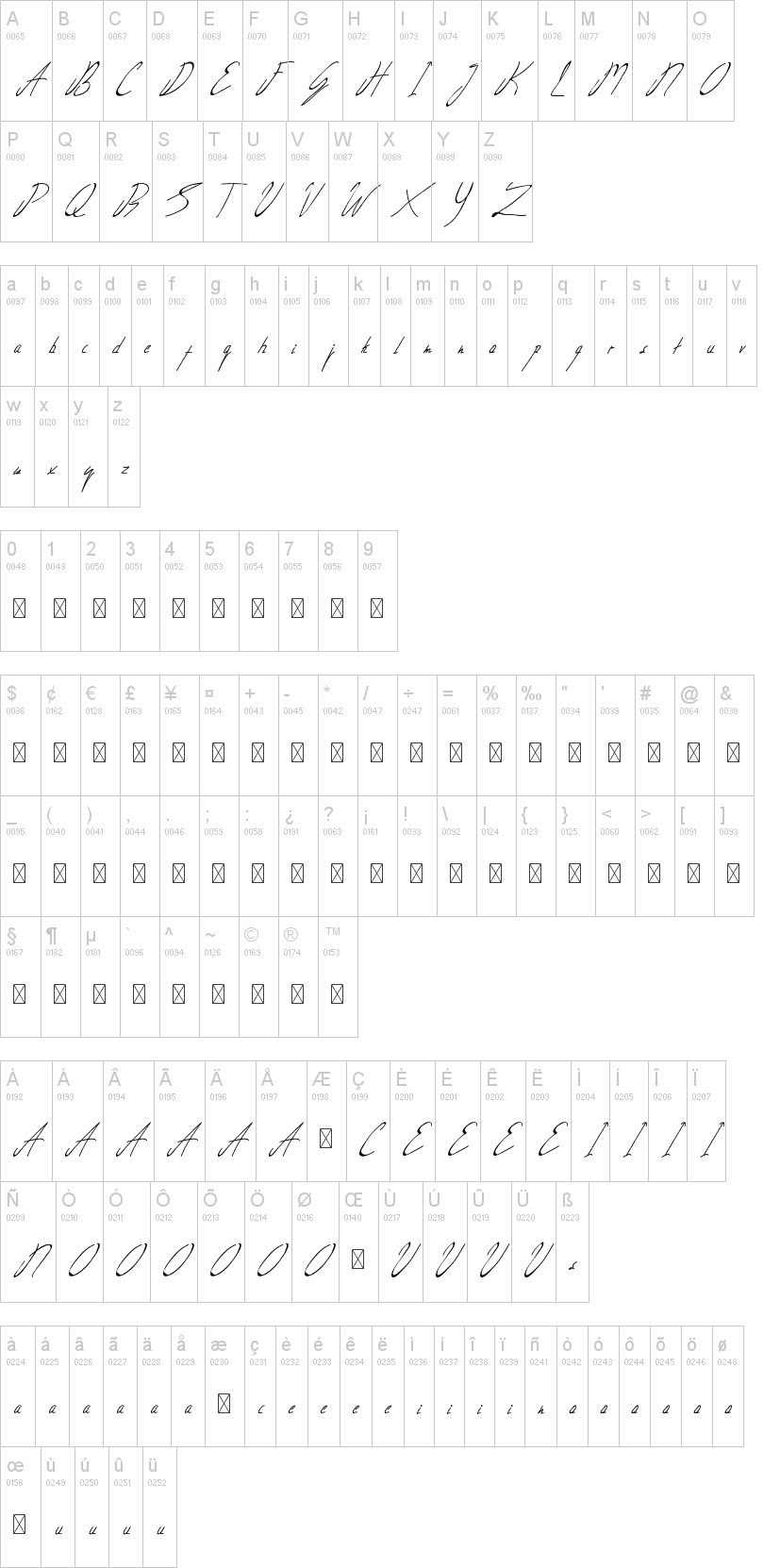
Livingston 字体是一款精致的英文字体,由设计师Paul D. Hunt发明,它的特点是清晰、简洁、精致。它采用圆滑的曲线,使字体看起来更加精致,更有美感,同时也更容易被识别。Livingston字体可以用于商业文档、广告、标题和其他印刷品上,体现出优雅、简洁、大气的特点。内容介绍
Livingston是一款非常不错的手写艺术字体,具有很好的视觉感,适合于文化类的宣传设计、商业类品牌的广告和产品包装设计以及个性化文字排版等较多场景。